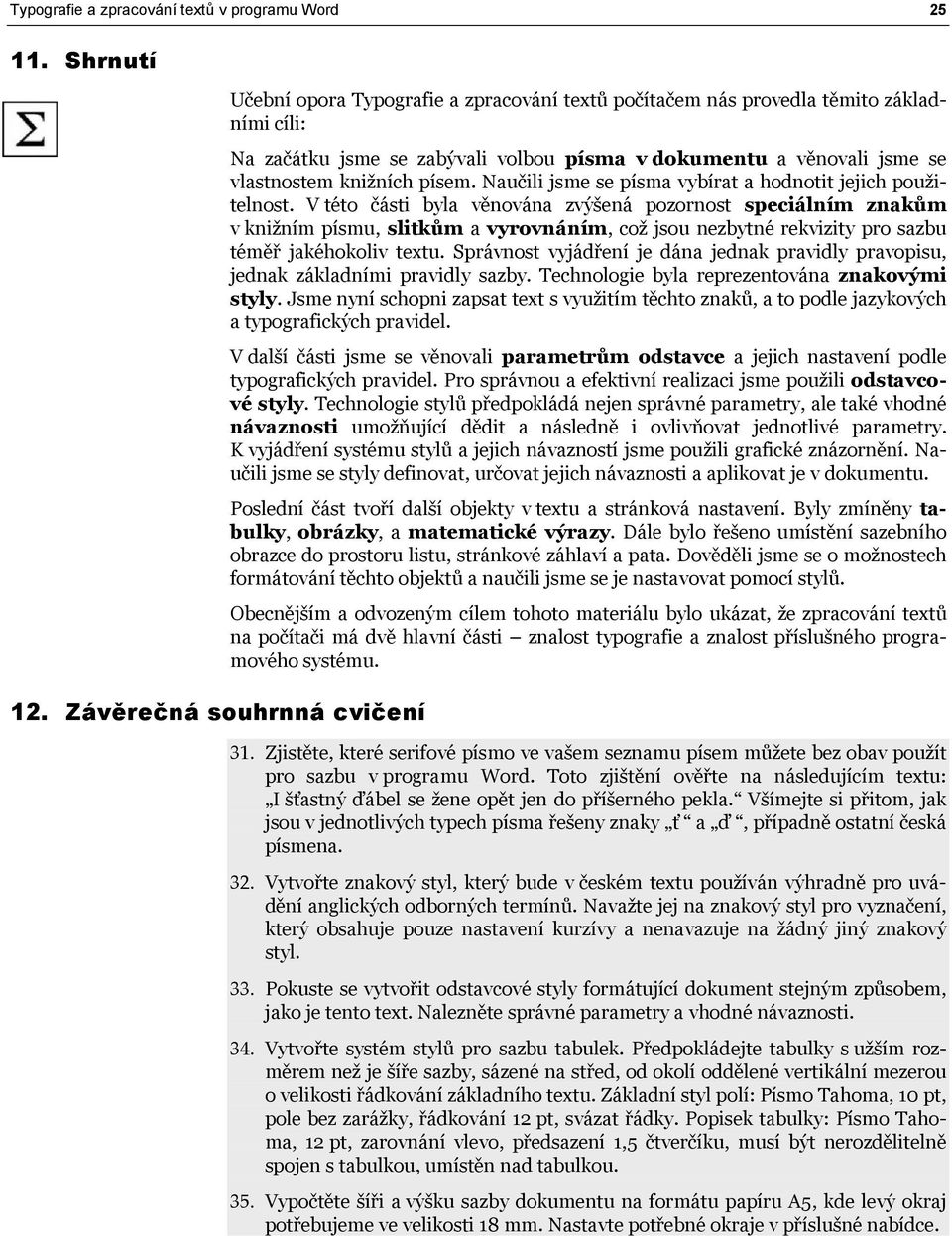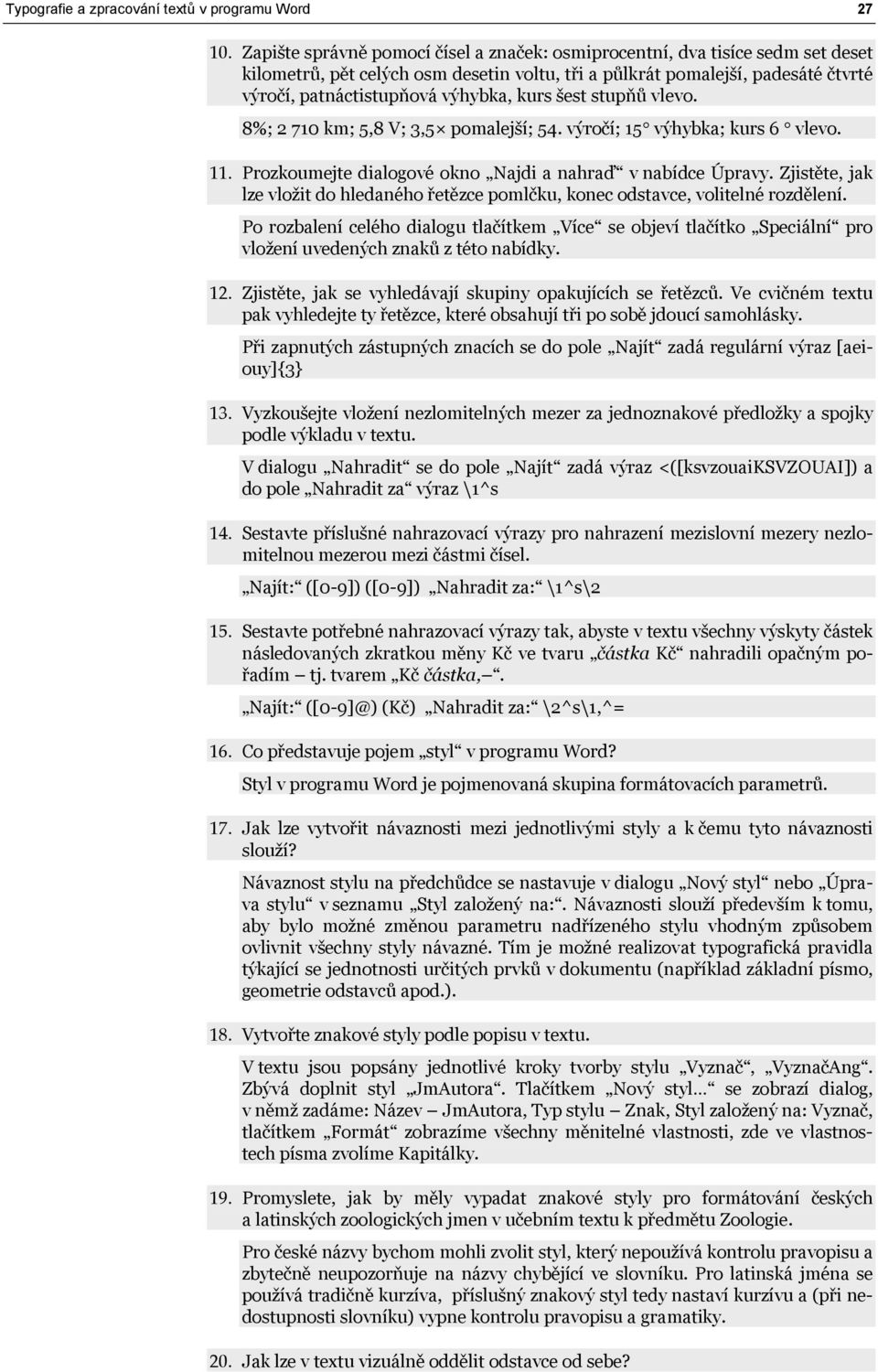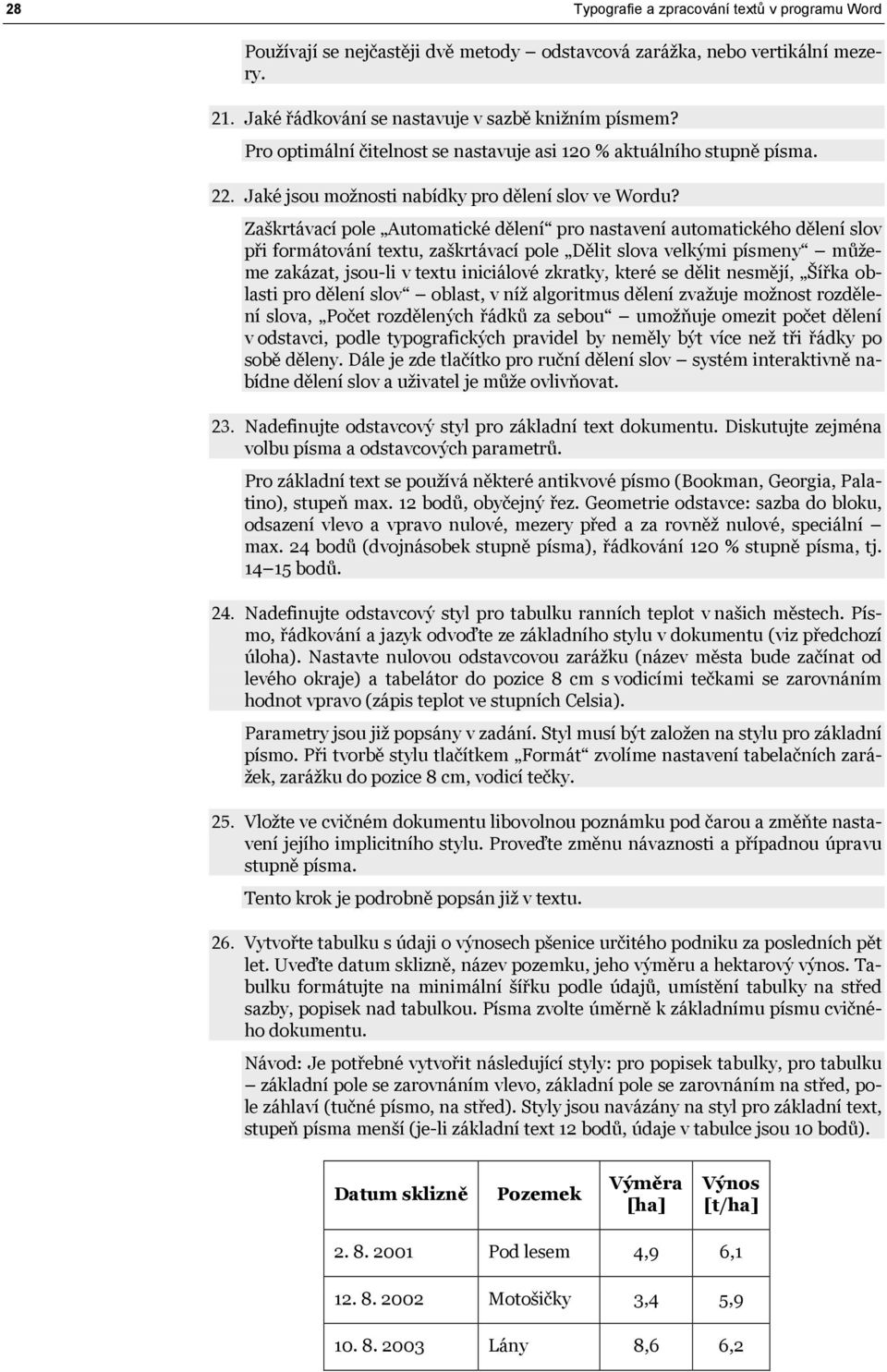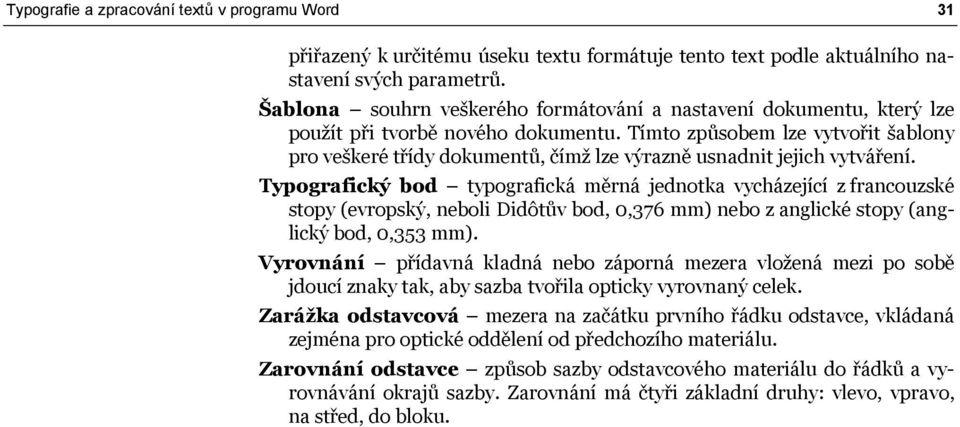
11. Shrnutí. 12. Závěrečná souhrnná cvičení. Učební opora Typografie a zpracování textů počítačem nás provedla těmito základními
1 Typografie a zpracování textů v programu Word Shrnutí 1. Závěrečná souhrnná cvičení Učební opora Typografie a zpracování textů počítačem nás provedla těmito základními cíli: Na začátku jsme se zabývali volbou písma v dokumentu a věnovali jsme se vlastnostem knižních písem. Naučili jsme se písma vybírat a hodnotit jejich použitelnost. V této části byla věnována zvýšená pozornost speciálním znakům v knižním písmu, slitkům a vyrovnáním, což jsou nezbytné rekvizity pro sazbu téměř jakéhokoliv textu. Správnost vyjádření je dána jednak pravidly pravopisu, jednak základními pravidly sazby. Technologie byla reprezentována znakovými styly. Jsme nyní schopni zapsat text s využitím těchto znaků, a to podle jazykových a typografických pravidel. V další části jsme se věnovali parametrům odstavce a jejich nastavení podle typografických pravidel. Pro správnou a efektivní realizaci jsme použili odstavcové styly. Technologie stylů předpokládá nejen správné parametry, ale také vhodné návaznosti umožňující dědit a následně i ovlivňovat jednotlivé parametry. K vyjádření systému stylů a jejich návazností jsme použili grafické znázornění. Naučili jsme se styly definovat, určovat jejich návaznosti a aplikovat je v dokumentu. Poslední část tvoří další objekty v textu a stránková nastavení. Byly zmíněny tabulky, obrázky, a matematické výrazy. Dále bylo řešeno umístění sazebního obrazce do prostoru listu, stránkové záhlaví a pata. Dověděli jsme se o možnostech formátování těchto objektů a naučili jsme se je nastavovat pomocí stylů. Obecnějším a odvozeným cílem tohoto materiálu bylo ukázat, že zpracování textů na počítači má dvě hlavní části znalost typografie a znalost příslušného programového systému. 31. Zjistěte, které serifové písmo ve vašem seznamu písem můžete bez obav použít pro sazbu v programu Word. Toto zjištění ověřte na následujícím textu: I šťastný ďábel se žene opět jen do příšerného pekla. Všímejte si přitom, jak jsou v jednotlivých typech písma řešeny znaky ť a ď, případně ostatní česká písmena. 3. Vytvořte znakový styl, který bude v českém textu používán výhradně pro uvádění anglických odborných termínů. Navažte jej na znakový styl pro vyznačení, který obsahuje pouze nastavení kurzívy a nenavazuje na žádný jiný znakový styl. 33. Pokuste se vytvořit odstavcové styly formátující dokument stejným způsobem, jako je tento text. Nalezněte správné parametry a vhodné návaznosti. 34. Vytvořte systém stylů pro sazbu tabulek. Předpokládejte tabulky s užším rozměrem než je šíře sazby, sázené na střed, od okolí oddělené vertikální mezerou o velikosti řádkování základního textu. Základní styl polí: Písmo Tahoma, 10 pt, pole bez zarážky, řádkování 1 pt, svázat řádky. Popisek tabulky: Písmo Tahoma, 1 pt, zarovnání vlevo, předsazení 1,5 čtverčíku, musí být nerozdělitelně spojen s tabulkou, umístěn nad tabulkou. 35. Vypočtěte šíři a výšku sazby dokumentu na formátu papíru A5, kde levý okraj potřebujeme ve velikosti 18 mm. Nastavte potřebné okraje v příslušné nabídce.
2 6 Typografie a zpracování textů v programu Word 13. Klíč k průběžným ověřovacím testům 1. Jak se liší knižní a strojopisné písmo? Základním rysem knižního písma je proporcionalita, tedy fakt, že každý znak zabírá jinou šířku. Strojopisné písmo vyhrazuje pro každý znak šířku stejnou (i pro mezeru), tato velikost se nazývá úhoz a má pro standardní psací stroj velikost 1/10 palce. Další podstatnou odlišností je znakový repertoár v knižním písmu existuje množina speciálních znaků, která ve strojopisném písmu chybí. Třetí podstatnou odlišností je existence různých řezů, stupňů a typů v knižním písmu, strojopis těmito možnostmi nedisponuje.. Který typ knižního písma použijete pro základní text většiny dokumentů? Pro základní text většiny dokumentů se používá antikvové (serifové, patkové) písmo (v nabídce programu Word například Palatino, Bookman, Georgia). 3. K čemu lze použít grotesk? Groteskové (bezserifové, bezpatkové) písmo se pro svou výraznost nejčastěji používá pro nadpisy v dokumentu, orientační tabule, akcidenční a reklamní tiskoviny. Ve větším textovém objemu se čte hůře než písmo antikvové. 4. Jaký typ písma můžeme použít pro příležitostné tiskoviny, například pozvánku na ples? Pro příležitostné (akcidenční) tiskoviny se používají kromě běžných typů i různá zdobená, kaligrafická, ručně psaná, gotická a podobná písma. Pro pozvánku na ples lze použít například kaligrafické písmo. 5. K čemu slouží písmové řezy? Jak se liší kurzíva a skloněné? Písmové řezy se používají často k vyznačování (zdůrazňování). K tomuto účelu slouží především kurzíva, dále pak tučný řez, pro vyznačování v tučném písmu pak také tučná kurzíva. Další řezy jsou určeny pro užití v celém dokumentu (nikoliv v kombinaci se základním řezem). Skloněný řez je jedním z řezů, které se na vyznačování nehodí, ale může sloužit pro různé příležitostné účely. Od kurzívy se liší kresbou znaků kurzíva má kresbu odlišnou od základního řezu, skloněné písmo nikoliv (kromě mechanického naklonění tahů). 6. Ve kterých případech použijete nezlomitelnou (ve Wordu pevnou) mezeru? Podle pravidel pravopisu je nezlomitelná mezera vkládána za jednoznakové předložky a spojky, za iniciálu s příjmením, mezi části (trojčíslí) čísla, mezi hodnotu a fyzikální jednotku ve zkratce a v některých dalších specifických případech, kdy není přípustné v daném místě rozdělení do dvou řádků. 7. V následující větě nahraďte otazníky správnými znaky (spojovník, pomlčka, příslušné mezery): Čtvrtý úryvek?ekonomicko?matematická cvičení, strany 3?8. Čtvrtý úryvek Ekonomicko-matematická cvičení, strany Jak správně oddělujeme mezerami závorky a uvozovky? Mezera se nikdy nepíše uvnitř uvozovek a uvnitř závorek. 9. Rozhodněte, zda jsou v následujících příkladech správně umístěny závorky a příslušná větná interpunkce: a) Pršelo (jako na jaře.) b) Kino bylo za rohem. (Jmenovalo se Oko.) c) Kino bylo za rohem (jmenovalo se Oko). a) chybně tečka patří za závorku, neboť patří k celé větě; b) správně; c) správně.
3 Typografie a zpracování textů v programu Word Zapište správně pomocí čísel a značek: osmiprocentní, dva tisíce sedm set deset kilometrů, pět celých osm desetin voltu, tři a půlkrát pomalejší, padesáté čtvrté výročí, patnáctistupňová výhybka, kurs šest stupňů vlevo. 8%; 710 km; 5,8 V; 3,5 pomalejší; 54. výročí; 15 výhybka; kurs 6 vlevo. 11. Prozkoumejte dialogové okno Najdi a nahraď v nabídce Úpravy. Zjistěte, jak lze vložit do hledaného řetězce pomlčku, konec odstavce, volitelné rozdělení. Po rozbalení celého dialogu tlačítkem Více se objeví tlačítko Speciální pro vložení uvedených znaků z této nabídky. 1. Zjistěte, jak se vyhledávají skupiny opakujících se řetězců. Ve cvičném textu pak vyhledejte ty řetězce, které obsahují tři po sobě jdoucí samohlásky. Při zapnutých zástupných znacích se do pole Najít zadá regulární výraz [aeiouy]{3} 13. Vyzkoušejte vložení nezlomitelných mezer za jednoznakové předložky a spojky podle výkladu v textu. V dialogu Nahradit se do pole Najít zadá výraz <([ksvzouai]) a do pole Nahradit za výraz \1^s 14. Sestavte příslušné nahrazovací výrazy pro nahrazení mezislovní mezery nezlomitelnou mezerou mezi částmi čísel. Najít: ([0-9]) ([0-9]) Nahradit za: \1^s\ 15. Sestavte potřebné nahrazovací výrazy tak, abyste v textu všechny výskyty částek následovaných zkratkou měny Kč ve tvaru částka Kč nahradili opačným pořadím tj. tvarem Kč částka,. Najít: ([0-9]@) (Kč) Nahradit za: \^s\1,^= 16. Co představuje pojem styl v programu Word? Styl v programu Word je pojmenovaná skupina formátovacích parametrů. 17. Jak lze vytvořit návaznosti mezi jednotlivými styly a k čemu tyto návaznosti slouží? Návaznost stylu na předchůdce se nastavuje v dialogu Nový styl nebo Úprava stylu v seznamu Styl založený na:. Návaznosti slouží především k tomu, aby bylo možné změnou parametru nadřízeného stylu vhodným způsobem ovlivnit všechny styly návazné. Tím je možné realizovat typografická pravidla týkající se jednotnosti určitých prvků v dokumentu (například základní písmo, geometrie odstavců apod.). 18. Vytvořte znakové styly podle popisu v textu. V textu jsou popsány jednotlivé kroky tvorby stylu Vyznač, VyznačAng. Zbývá doplnit styl JmAutora. Tlačítkem Nový styl se zobrazí dialog, v němž zadáme: Název JmAutora, Typ stylu Znak, Styl založený na: Vyznač, tlačítkem Formát zobrazíme všechny měnitelné vlastnosti, zde ve vlastnostech písma zvolíme Kapitálky. 19. Promyslete, jak by měly vypadat znakové styly pro formátování českých a latinských zoologických jmen v učebním textu k předmětu Zoologie. Pro české názvy bychom mohli zvolit styl, který nepoužívá kontrolu pravopisu a zbytečně neupozorňuje na názvy chybějící ve slovníku. Pro latinská jména se používá tradičně kurzíva, příslušný znakový styl tedy nastaví kurzívu a (při nedostupnosti slovníku) vypne kontrolu pravopisu a gramatiky. 0. Jak lze v textu vizuálně oddělit odstavce od sebe?
4 8 Typografie a zpracování textů v programu Word Používají se nejčastěji dvě metody odstavcová zarážka, nebo vertikální mezery. 1. Jaké řádkování se nastavuje v sazbě knižním písmem? Pro optimální čitelnost se nastavuje asi 10 % aktuálního stupně písma.. Jaké jsou možnosti nabídky pro dělení slov ve Wordu? Zaškrtávací pole Automatické dělení pro nastavení automatického dělení slov při formátování textu, zaškrtávací pole Dělit slova velkými písmeny můžeme zakázat, jsou-li v textu iniciálové zkratky, které se dělit nesmějí, Šířka oblasti pro dělení slov oblast, v níž algoritmus dělení zvažuje možnost rozdělení slova, Počet rozdělených řádků za sebou umožňuje omezit počet dělení v odstavci, podle typografických pravidel by neměly být více než tři řádky po sobě děleny. Dále je zde tlačítko pro ruční dělení slov systém interaktivně nabídne dělení slov a uživatel je může ovlivňovat. 3. Nadefinujte odstavcový styl pro základní text dokumentu. Diskutujte zejména volbu písma a odstavcových parametrů. Pro základní text se používá některé antikvové písmo (Bookman, Georgia, Palatino), stupeň max. 1 bodů, obyčejný řez. Geometrie odstavce: sazba do bloku, odsazení vlevo a vpravo nulové, mezery před a za rovněž nulové, speciální max. 4 bodů (dvojnásobek stupně písma), řádkování 10 % stupně písma, tj bodů. 4. Nadefinujte odstavcový styl pro tabulku ranních teplot v našich městech. Písmo, řádkování a jazyk odvoďte ze základního stylu v dokumentu (viz předchozí úloha). Nastavte nulovou odstavcovou zarážku (název města bude začínat od levého okraje) a tabelátor do pozice 8 cm s vodicími tečkami se zarovnáním hodnot vpravo (zápis teplot ve stupních Celsia). Parametry jsou již popsány v zadání. Styl musí být založen na stylu pro základní písmo. Při tvorbě stylu tlačítkem Formát zvolíme nastavení tabelačních zarážek, zarážku do pozice 8 cm, vodicí tečky. 5. Vložte ve cvičném dokumentu libovolnou poznámku pod čarou a změňte nastavení jejího implicitního stylu. Proveďte změnu návaznosti a případnou úpravu stupně písma. Tento krok je podrobně popsán již v textu. 6. Vytvořte tabulku s údaji o výnosech pšenice určitého podniku za posledních pět let. Uveďte datum sklizně, název pozemku, jeho výměru a hektarový výnos. Tabulku formátujte na minimální šířku podle údajů, umístění tabulky na střed sazby, popisek nad tabulkou. Písma zvolte úměrně k základnímu písmu cvičného dokumentu. Návod: Je potřebné vytvořit následující styly: pro popisek tabulky, pro tabulku základní pole se zarovnáním vlevo, základní pole se zarovnáním na střed, pole záhlaví (tučné písmo, na střed). Styly jsou navázány na styl pro základní text, stupeň písma menší (je-li základní text 1 bodů, údaje v tabulce jsou 10 bodů). Datum sklizně Pozemek Výměra [ha] Výnos [t/ha] Pod lesem 4,9 6, Motošičky 3,4 5, Lány 8,6 6,
5 Typografie a zpracování textů v programu Word Na drahách 5,5 6, Za rybníkem, 6,0 7. Vytvořte dokument, v němž zapíšete vzorce pro goniometrické funkce polovičního a dvojnásobného úhlu. Všechny vzorce formátujte na střed s vertikální mezerou o polovině řádkování základního textu. Nastavte v editoru rovnic písmo odpovídající základnímu písmu dokumentu (jiné než Times New Roman). V následujících výrazech je jako základní písmo nastaveno Georgia stejně jako v okolním textovém materiálu. Při těchto nastaveních je však třeba brát v úvahu i skutečnost, zda se základní písmo dokumentu hodí pro matematická vyjádření, zda disponuje všemi potřebnými znaky apod. α sin = 1 cosα α 1+ cosα cos = sin α = sinα cosα cosα = cos α sin α 8. Vytvořte pomocí nabídky Kreslení zjednodušené organizační schéma fakulty (děkan, proděkani, vedoucí ústavů, učitelé, techničtí pracovníci). Takto vytvořený obrázek vložte do textu a vyzkoušejte umístění pomocí vlastního umisťovacího stylu (na střed sazby, vertikální mezery o velikosti řádkování). děkan vedoucí ústavů proděkani učitelé techničtí pracovníci 9. Ve svém cvičném dokumentu nastavte stránku o velikosti A5, okraje zvolte podle známého poměru s tím, že dolní okraj potřebujete 35 mm. Využijeme poměru mezi okraji 3:4:5:7. Je-li tedy dolní okraj 35 mm, pak levý okraj je 15 mm, horní okraj 0 mm a pravý okraj 5 mm. 30. Nastavte stránkovou patu s číslem stránky na vnějším okraji. Výpis čísla stránky ovlivněte znakovým stylem Folio, styl pro stránkovou patu odvoďte od základního stylu v dokumentu.
6 30 Typografie a zpracování textů v programu Word 14. Slovníček nových pojmů Postup je popsán v textu. Styl Folio je znakovým stylem, nastavuje například tučné písmo, ale je založen na položce (standardní vlastnosti). Tím přebírá písmo ze svého okolí, kde je použit. K tomu je potřeba změnit styl pro stránkovou patu Zápatí, kde je potřeba změnit návaznost. Místo stylu Normální je potřebné styl Zápatí navázat na styl, kterým se formátuje základní text dokumentu. Antikva druh knižního písma, který obsahuje serify a stíny (jinak též serifové, patkové písmo). Čtverčík relativní typografická měrná jednotka, je rovna stupni použitého písma. Formátování úprava textu do požadované podoby, úpravy spočívají ve vkládání formátovacích příkazů zvolenému úseku textu nebo nastavování parametrů sazby (okraje, dělení slov apod.). Grotesk druh knižního písma, který nemá ani serify, ani stíny (jinak též bezserifové, bezpatkové písmo). Knižní písmo písmo, které bylo vytvořeno pro profesionální sazbu dokumentů. Dříve bylo používáno v tzv. kovové (horké) sazbě, kde byly litery odlévány z kovu a ručně skládány do řádků a stránek. Základním parametrem knižního písma je, že každý znak má jinou šíři. Neproporcionální písmo jiný název pro strojopisné písmo. Odstavec úsek textu obsahující ucelenou myšlenku. Dělení textu do odstavců stanovuje autor textu. Úkolem úpravce je vizuálně odlišit odstavce od sebe a od okolního materiálu (obrázků, tabulek, záhlaví ). Odstavcová geometrie parametry odstavce upravující jeho rozměry a způsob sazby. Jde o zarážku, odsazení, okraje, řádkování. Písmový řez modifikace základního tvaru písma pro získání odlišného vzhledu, často použitelného pro vyznačování (kurzíva, tučné). Písmový stupeň velikost kresby písma udávaná v typografických bodech. Původně to byl rozměr kovové litery, na níž byl příslušný typ písma odlit. Proporcionální písmo jiný název pro knižní písmo. Půlčtverčík relativní typografická měrná jednotka. Je rovna polovině čtverčíku. Regulární výraz výraz popisující množinu řetězců sestavenou podle určitých pravidel. V regulárním výrazu se používají tzv. zástupné znaky tj. znaky, které zastupují proměnnou část (například libovolnou číslici, libovolnou skupinu znaků) nebo určité speciální místo (například začátek slova). Řádkování vzdálenost mezi dvěma stejnolehlými body dvou po sobě jdoucích řádků v odstavci. Velikost řádkování je určena především stupněm použitého písma, za optimální hodnotu se považuje 1, čtverčíku. Slitek znak, který vzniká spojením původně samostatných znaků, ale který tvoří grafický celek pro dosažení esteticky přijatelného výsledku. Nejčastěji používaným slitkem je fi. U některých slitků vzniklých v dřívějších dobách dnes původní znaky nerozeznáváme, příkladem je znak & složený původně z písmen et (latinská spojka a ). Speciální znaky souhrnné pracovní označení pro znaky, které se používají v knižním písmu, ale používají se jiným způsobem než na psacím stroji. Jedná se o různé druhy mezer, pomlčky, spojovníky, uvozovky, závorky, výpustky apod. Strojopisné písmo písmo, jehož základním rysem je stejná šíře každého znaku včetně mezery. Vzniklo výrazným zjednodušením knižního písma z technických důvodů při konstrukci psacího stroje. Kromě identické šířky každého znaku ještě neobsahuje řadu speciálních znaků a při jeho použití nejsou k dispozici různé typy, stupně a řezy. Styl (pojem v programu Word) je pojmenovaná skupina formátovacích parametrů. Styly mohou být různých typů (odstavcové, znakové a další). Styl
7 Typografie a zpracování textů v programu Word 31 přiřazený k určitému úseku textu formátuje tento text podle aktuálního nastavení svých parametrů. Šablona souhrn veškerého formátování a nastavení dokumentu, který lze použít při tvorbě nového dokumentu. Tímto způsobem lze vytvořit šablony pro veškeré třídy dokumentů, čímž lze výrazně usnadnit jejich vytváření. Typografický bod typografická měrná jednotka vycházející z francouzské stopy (evropský, neboli Didôtův bod, 0,376 mm) nebo z anglické stopy (anglický bod, 0,353 mm). Vyrovnání přídavná kladná nebo záporná mezera vložená mezi po sobě jdoucí znaky tak, aby sazba tvořila opticky vyrovnaný celek. Zarážka odstavcová mezera na začátku prvního řádku odstavce, vkládaná zejména pro optické oddělení od předchozího materiálu. Zarovnání odstavce způsob sazby odstavcového materiálu do řádků a vyrovnávání okrajů sazby. Zarovnání má čtyři základní druhy: vlevo, vpravo, na střed, do bloku.